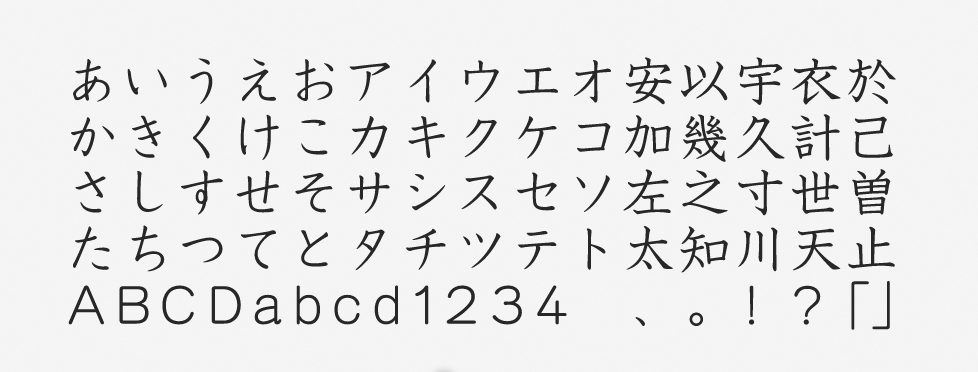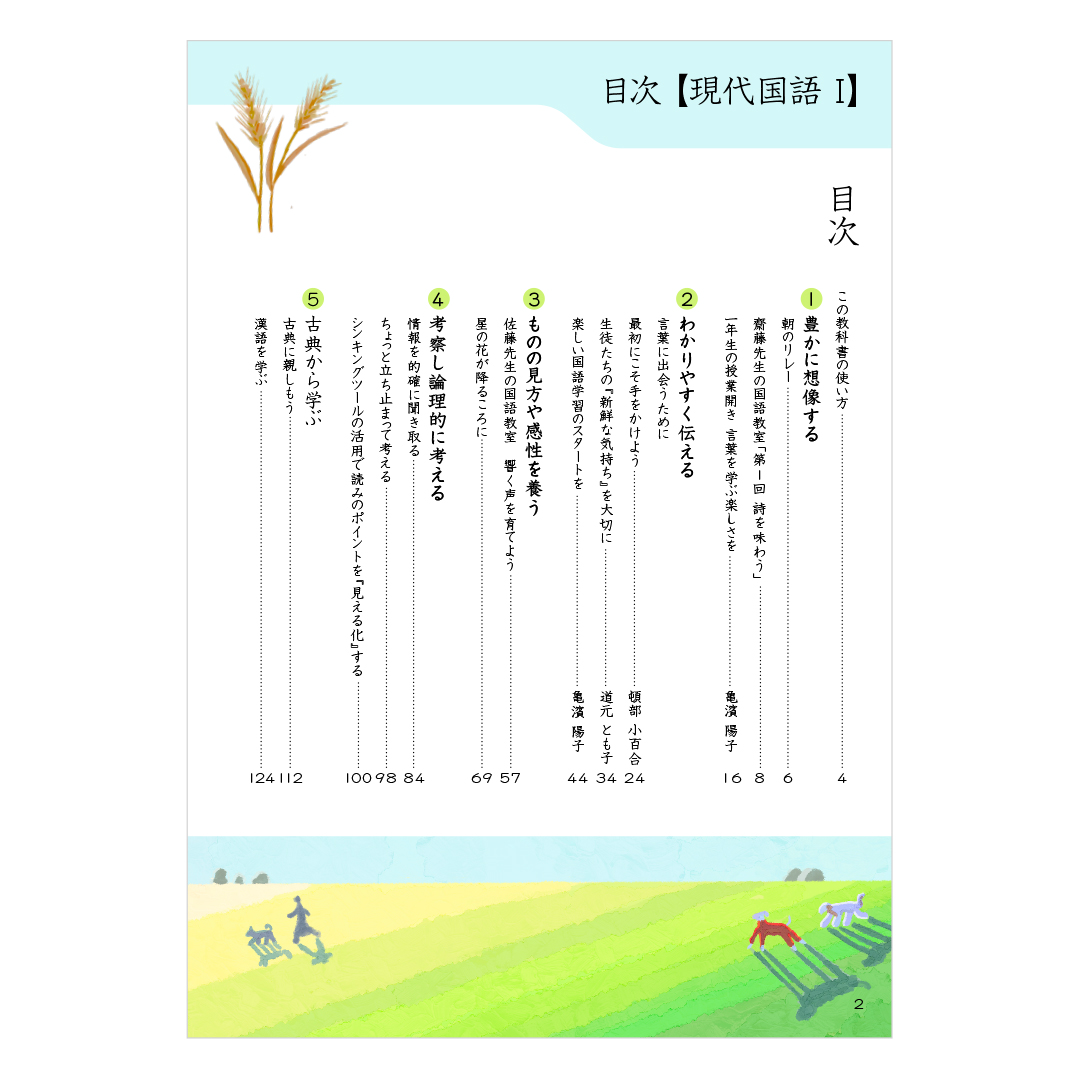
「教科書ICA」について
教科書体は楷書体から生まれ、分かりやすい字画へと整理されてきました。現代では毛筆の勢いを抑え、鉛筆やペンで書くような書風であることが一般的です。その教科書体の1つである教科書ICAは、教育分野には必須のフォント。学参書体は、常用漢字のデザインが、文部科学省の学習指導要領の「代表的な字形」に準拠したものに統一されています。
「教科書ICA」の特徴
字を習うための規範となる形が素直に表されたフォントです。教科書や参考書、副読本、学習塾のテキストなどに安心して使用できます。
通常書体では、画数、はね、押さえ、とめなど、書体によって字体の表現の異なる文字が共通の字形に統一されており、学習に便利なフォントであることはもちろん、絵本や玩具などにも有効です。ただし、可愛らしさはなく、すっきりとした印象に仕上がります。
教育に関する印刷物では、迷わずに使えるフォントです。手書き文字の筆跡に近い書体であるため、文字を覚えるプロセスにおいて必要なフォントと言えるでしょう。作例は教科書の一部であるため、素直に教科書ICAを採用しました。小さな文字でも、しっかりと読みやすいフォントです。